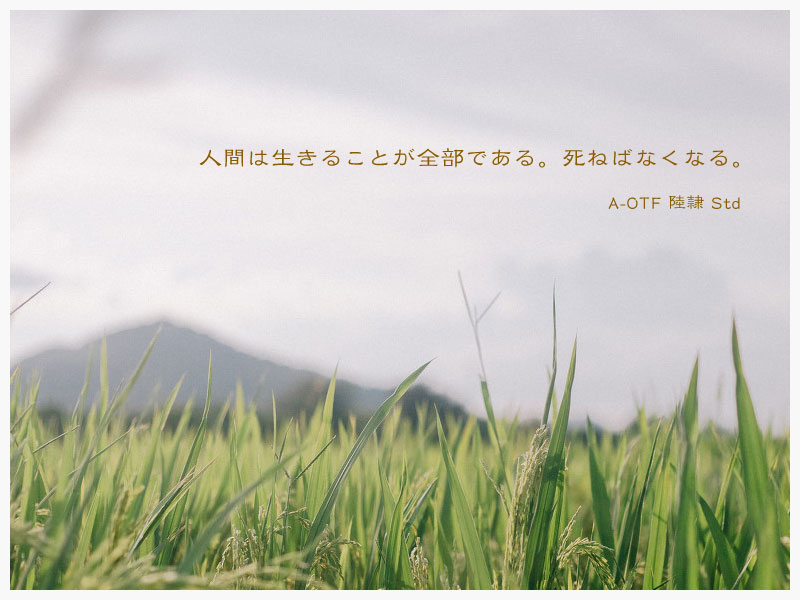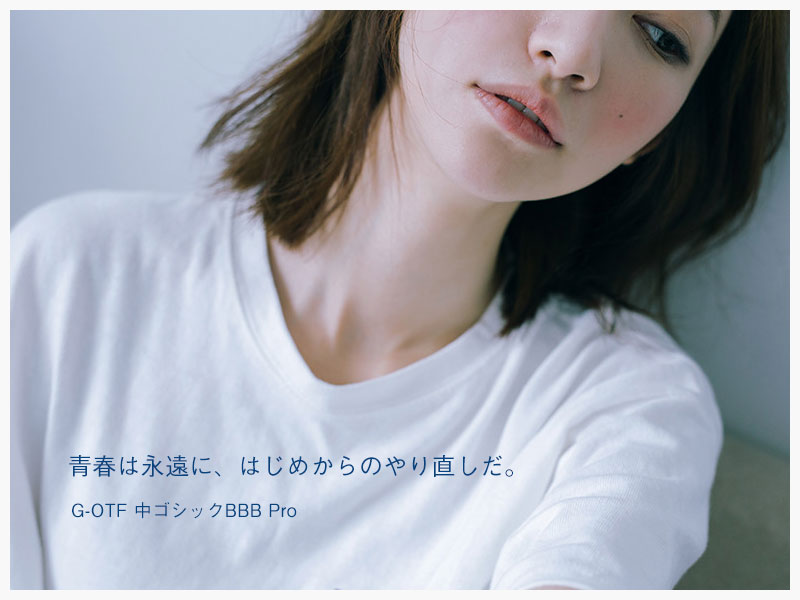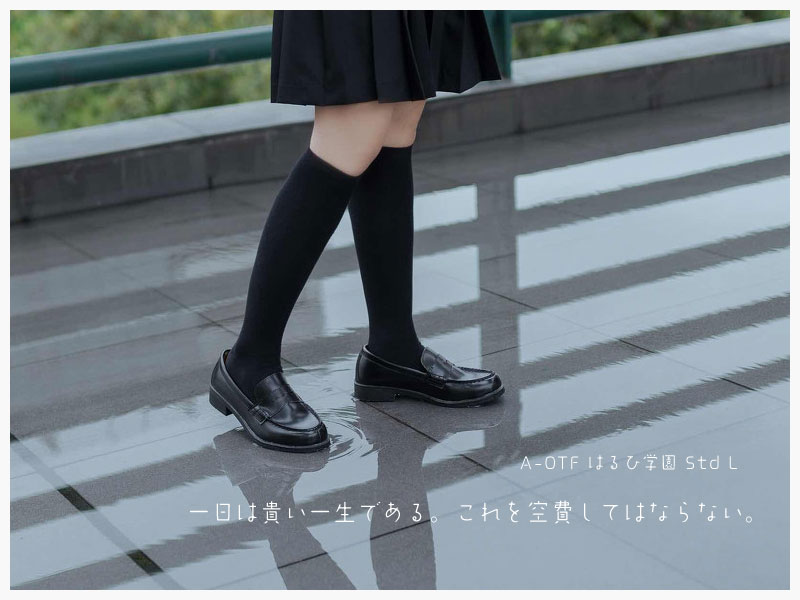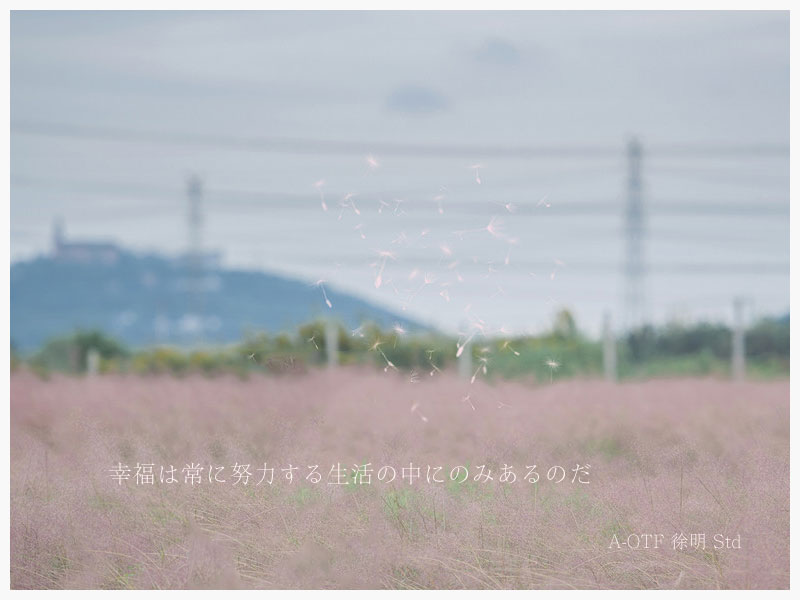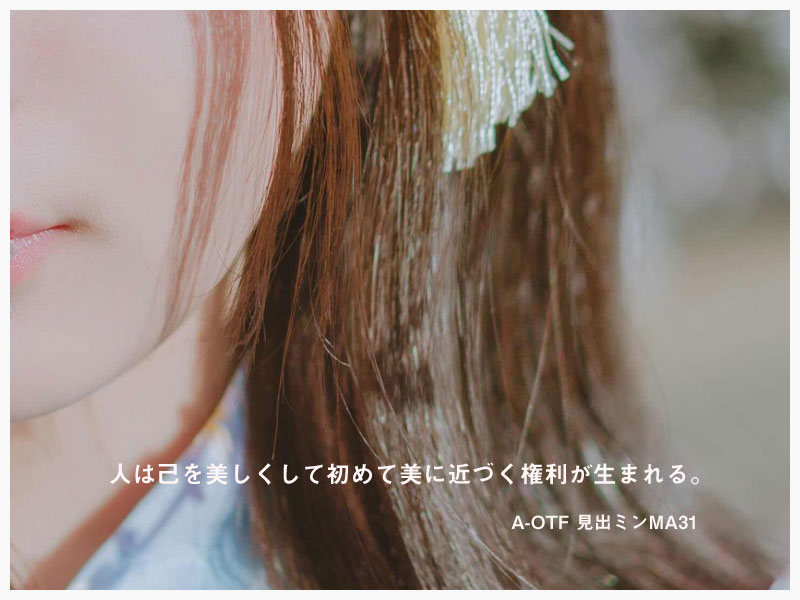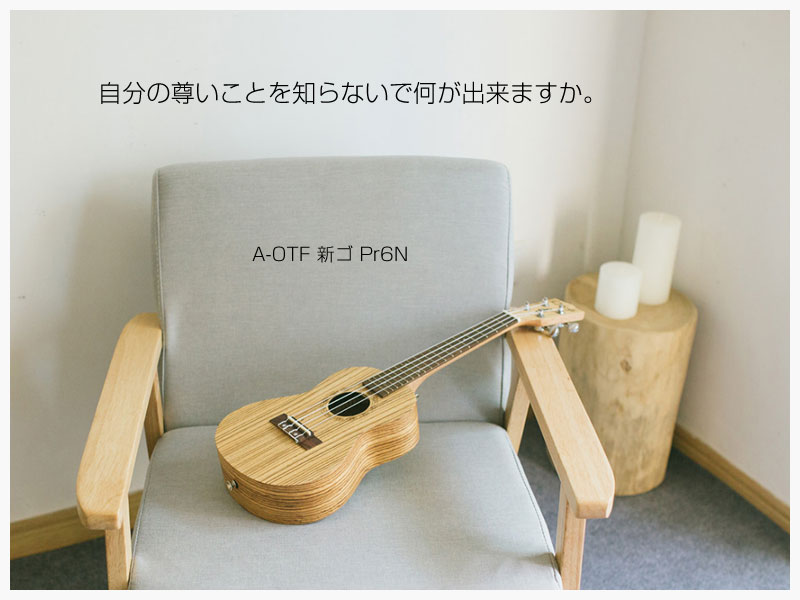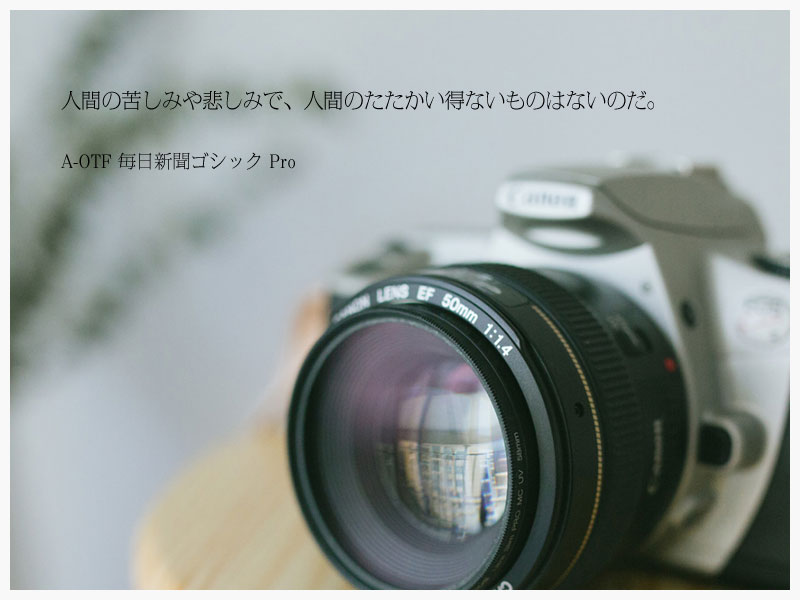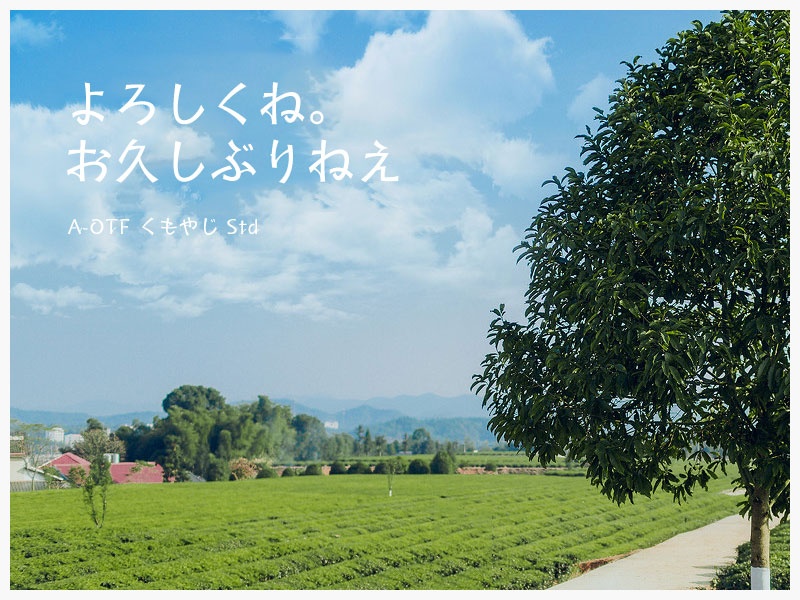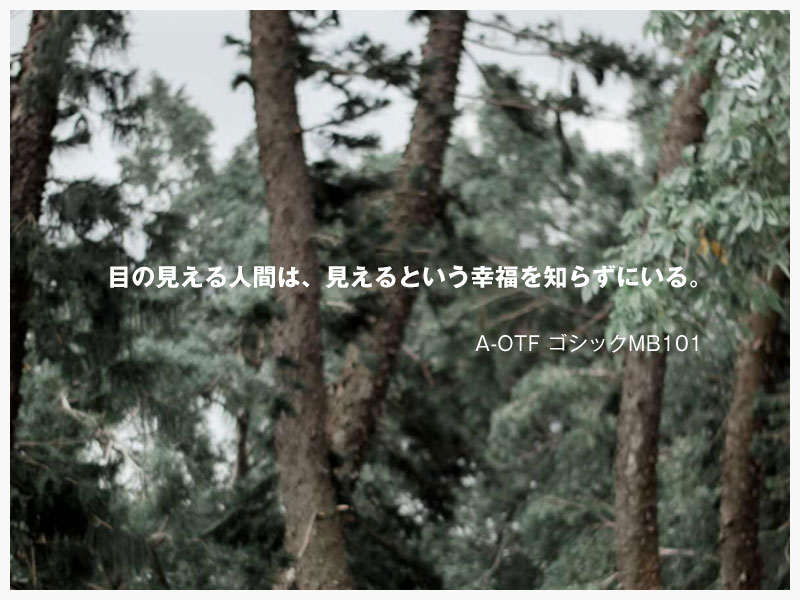
10款小清新风格日文字体合集
对于设计师而言,日本字体具有很高的实用价值和参考价值。素材君自己也很喜欢小清新风格字体,整理了10款日文字体,搭配唯美伤感的文字,很有味道,值得收藏。
A-OTF 教科書ICA
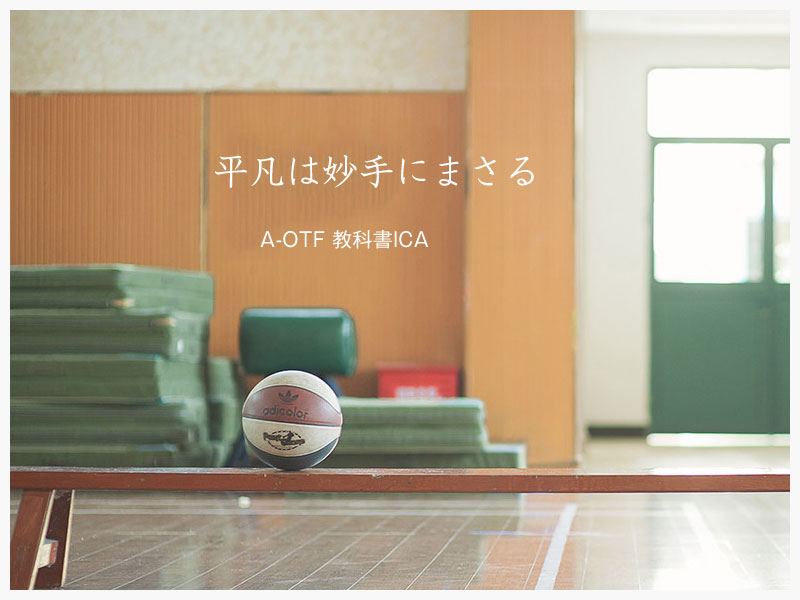
A-OTF 陸隷 Std
G-OTF 中ゴシックBBB Pro
A-OTF はるひ学園 Std L
A-OTF 徐明 Std
A-OTF 見出ミンMA31
A-OTF 新ゴ Pr6N
A-OTF 毎日新聞ゴシック Pro
A-OTF くもやじ Std
A-OTF ゴシックMB101
日文字体也可以打出中文,只不过可能会出现缺字,很多人不知道,用日本字体有部分字是需要打成繁体字的,如果缺字了,是可以在AI 里转成曲线,重新拼字。